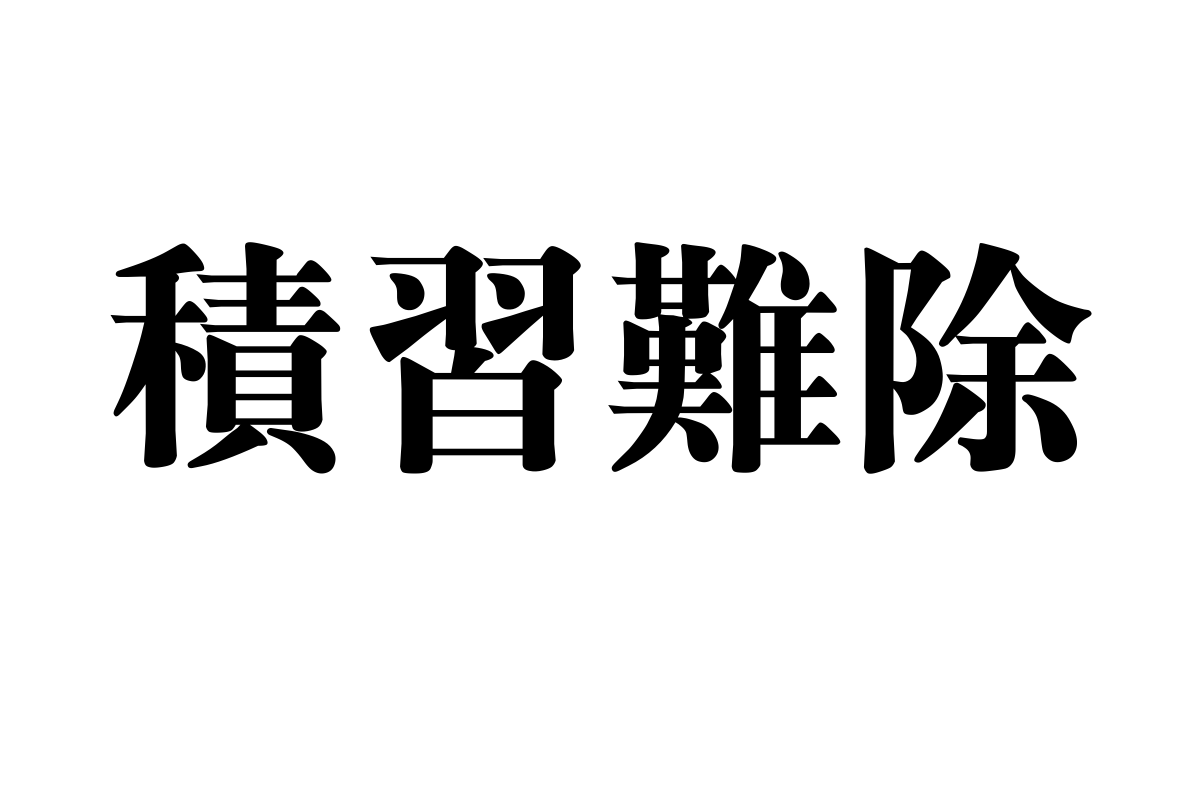
汉仪粗宋繁字体是一款具有现代感和实用性的中文字体。它的特点是字形粗壮,笔画清晰,结构紧凑,易于阅读和书写。这种字体适合用于各种需要强调文字清晰度和易读性的场合,如广告、海报、书籍等。
汉仪粗宋繁字体的特点包括:
– 字形粗壮,笔画清晰,结构紧凑;
– 适用于各种需要强调文字清晰度和易读性的场合;
– 适合用于广告、海报、书籍等。
总的来说,汉仪粗宋繁字体是一款实用的中文字体,能够满足用户在各种场合下对文字清晰度和易读性的需求。